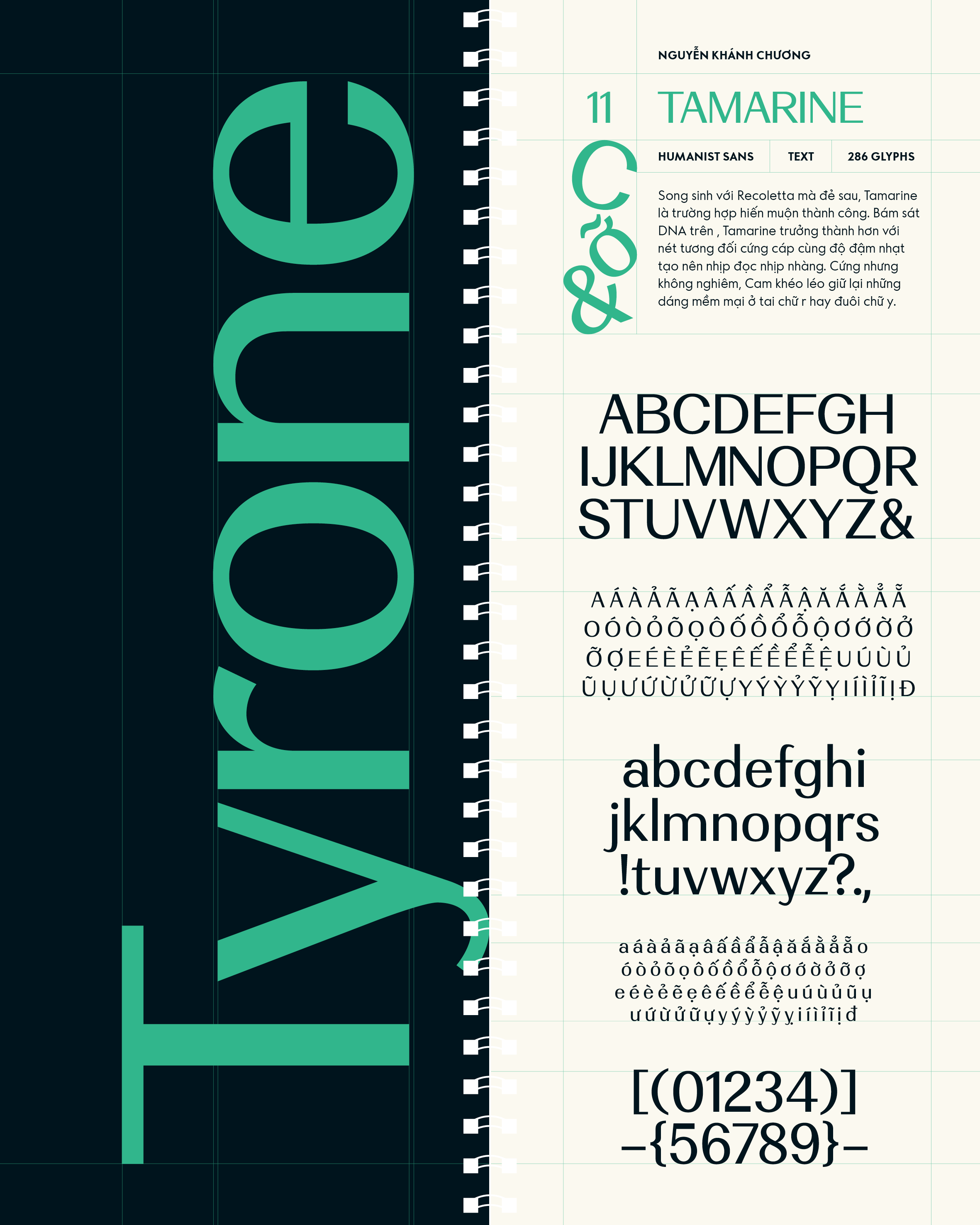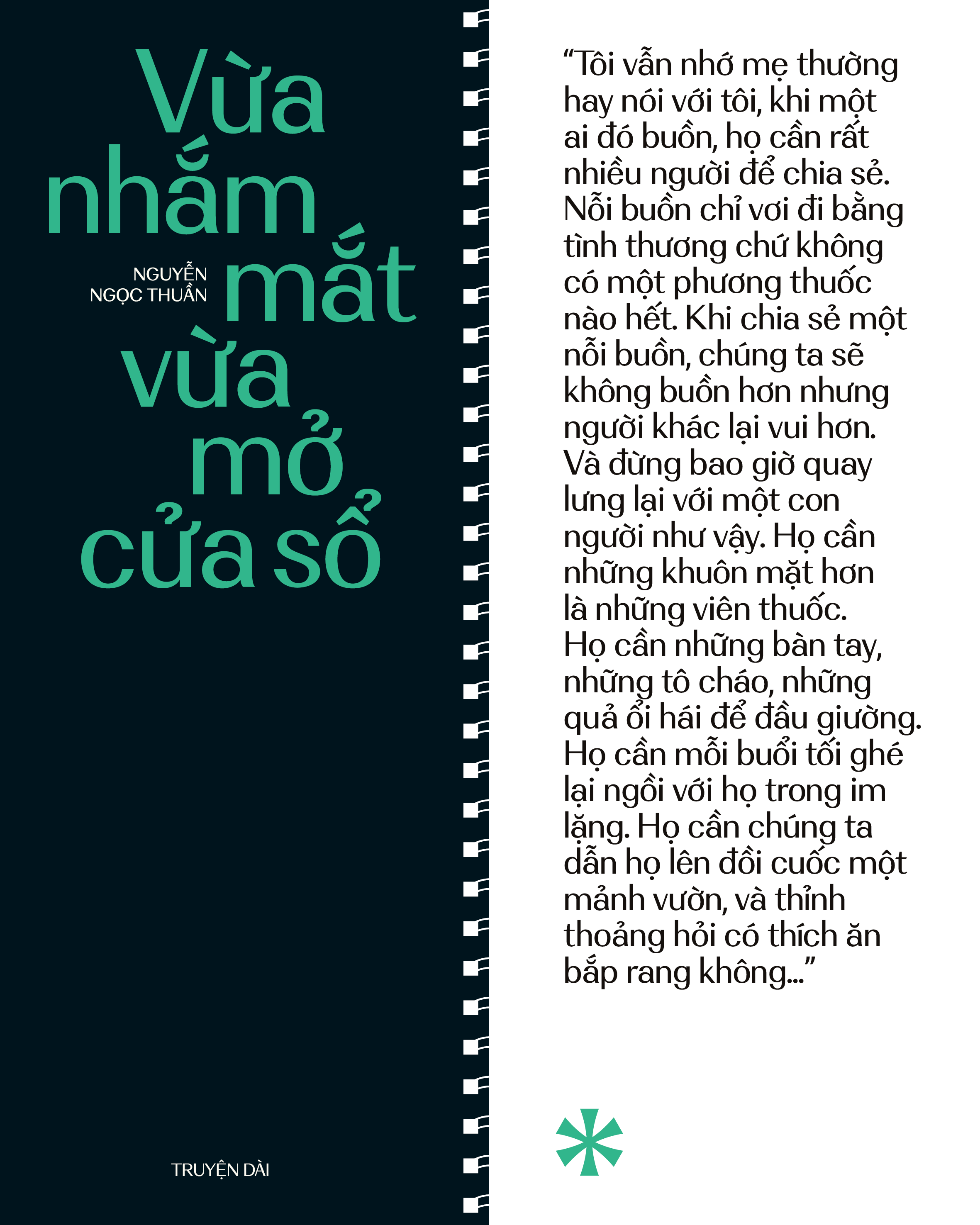
Tamarine
Về Tamarine: Song sinh với Recoletta mà đẻ sau, Tamarine là trường hợp hiến muộn thành công. Bám sát DNA trên , Tamarine trưởng thành hơn với nét tương đối cứng cáp cùng độ đậm nhạt tạo nên nhịp đọc nhịp nhàng. Cứng nhưng không nghiêm, Cam khéo léo giữ lại những dáng mềm mại ở tai chữ r hay đuôi chữ y.
Humanist Sans-serif
Display
Nguyễn Khánh Chương